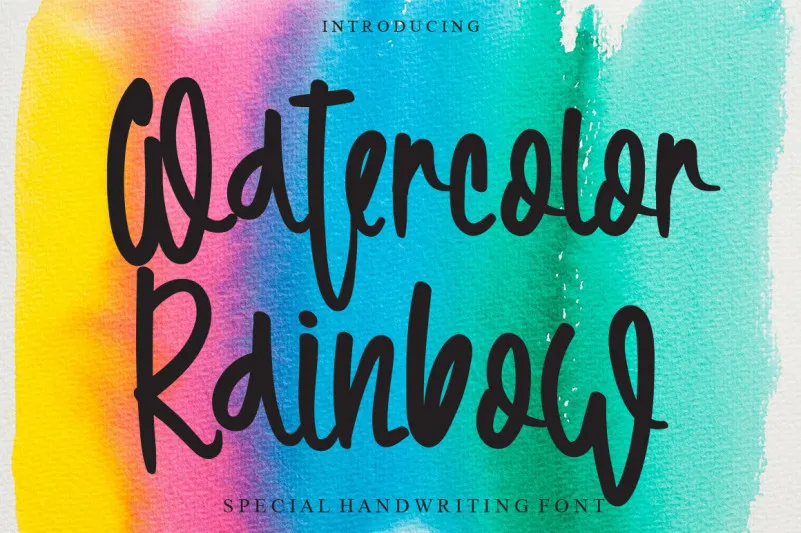
Watercolor Rainbow Font – Fonte Grátis
Watercolor Rainbow Font
Esta é uma fonte escrita a mão simpática que traz um charme cívilizadinho e fluido. Através dela você pode criar algo tão brilhante e original quanto um espetáculo de cores no céu à noite. Se apaixone por esta fonte e use-a em seus projetos mais criativos, eles certamente vão brilhar ainda mais. Sua designer, LevinCreative, trouxe para você este estilo único que ilumina qualquer texto com sua luz cintilante e mágica. Ideal tanto para textos quanto para gráficos, a Watercolor Rainbow Font é uma escolha perfeita para quem valoriza tanto o equilíbrio elegante quanto a diversão criativa em seus projetos.